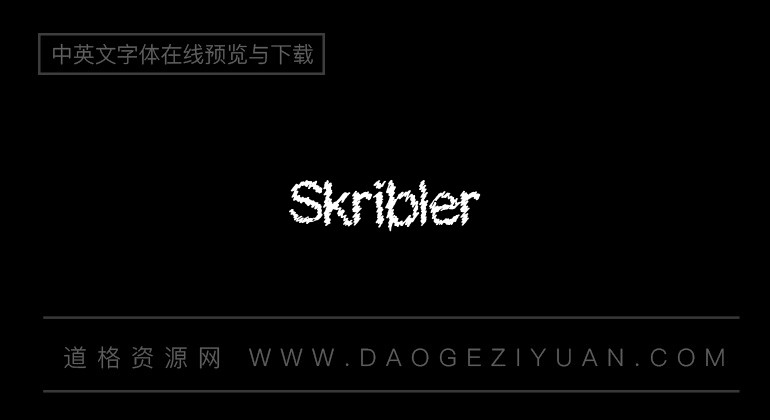
Skribler
Skribler字体是一种非常有趣的手写风格字体,它的特点是笔画流畅,仿佛是一个人在纸上书写的感觉。这种字体通常被用于设计和艺术项目中,尤其是那些需要一些个性化或是自然感觉的场合。 Skribler字体有多种不同类型,包括有一些非常大胆有力的字体,也有一些细致而柔和的字体。这种字体的设计灵感来源于人们的日常书写,以及艺术家们对于手写字体的热爱。它们通常被用于广告、海报、标志、包装、书籍、杂志、宣传册等设计领域,以增加视觉效果和吸引人的注意力。 总之,Skribler字体是一款非常有趣和个性化的字体,它能够很好的传达出人们在书写时的自然感觉和灵活性。无论是在个人还是商业项目中,使用Skribler字体都可以为你的作品增加一份独特和吸引人的气息。
Skribler是一款非常不错的手写艺术字体,具有很好的视觉感,适合于文化类的宣传设计、商业类品牌的广告和产品包装设计以及个性化文字排版等较多场景。